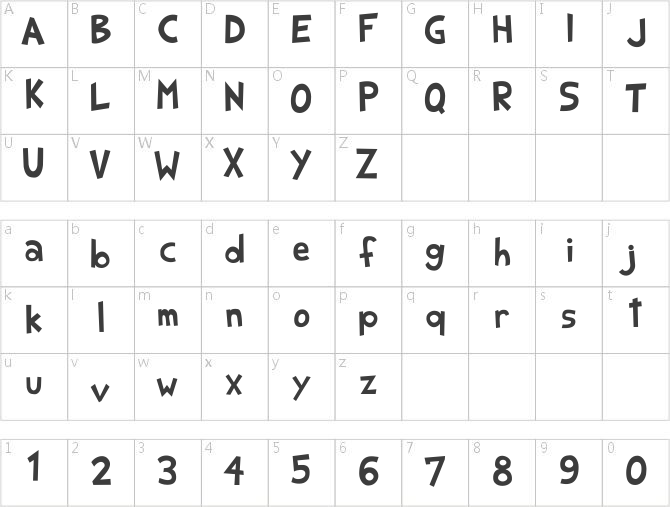
Shark Random Funnyness 2 詳情頁
Shark Random Funnyness 2字體字庫是一款讓人賞心悅目、百看不厭的英文字體,適合各類廣告和產(chǎn)品包裝設(shè)計應(yīng)用,字體大小0.02MB,格式為ttf字體,上傳用戶是sygyve520,作者/版權(quán)方為未知